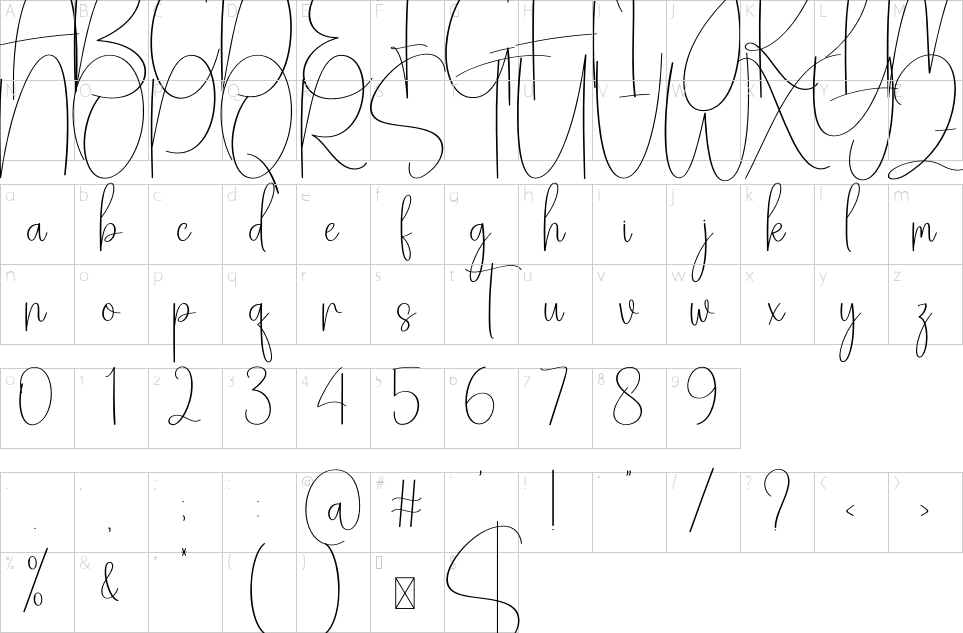
A fonte Autography é uma opção excelente para designers e profissionais de mídia que buscam uma fonte clara e elegante para seus trabalhos. Desenvolvida por scratchones, essa fonte foi projetada para criar textos agradáveis e facilmente legíveis. Seu estilo moderno e minimalista faz dela uma escolha popular para o design gráfico, sendo particularmente útil para títulos e headlines. Os usuários podem facilmente baixar a Autography font tanto para sistemas Windows quanto para Mac, permitindo uma versatilidade que atende a uma gama ampla de necessidades. Com o uso da Autography font, você pode garantir que os seus textos sejam claros e profissionais, seja em um projeto de design ou em uma marca digital. Sua simplicidade não deixa de lado a beleza, fazendo-a uma fonte ideal para quem procura uma opção sem compromisso, sem perder em qualidade.